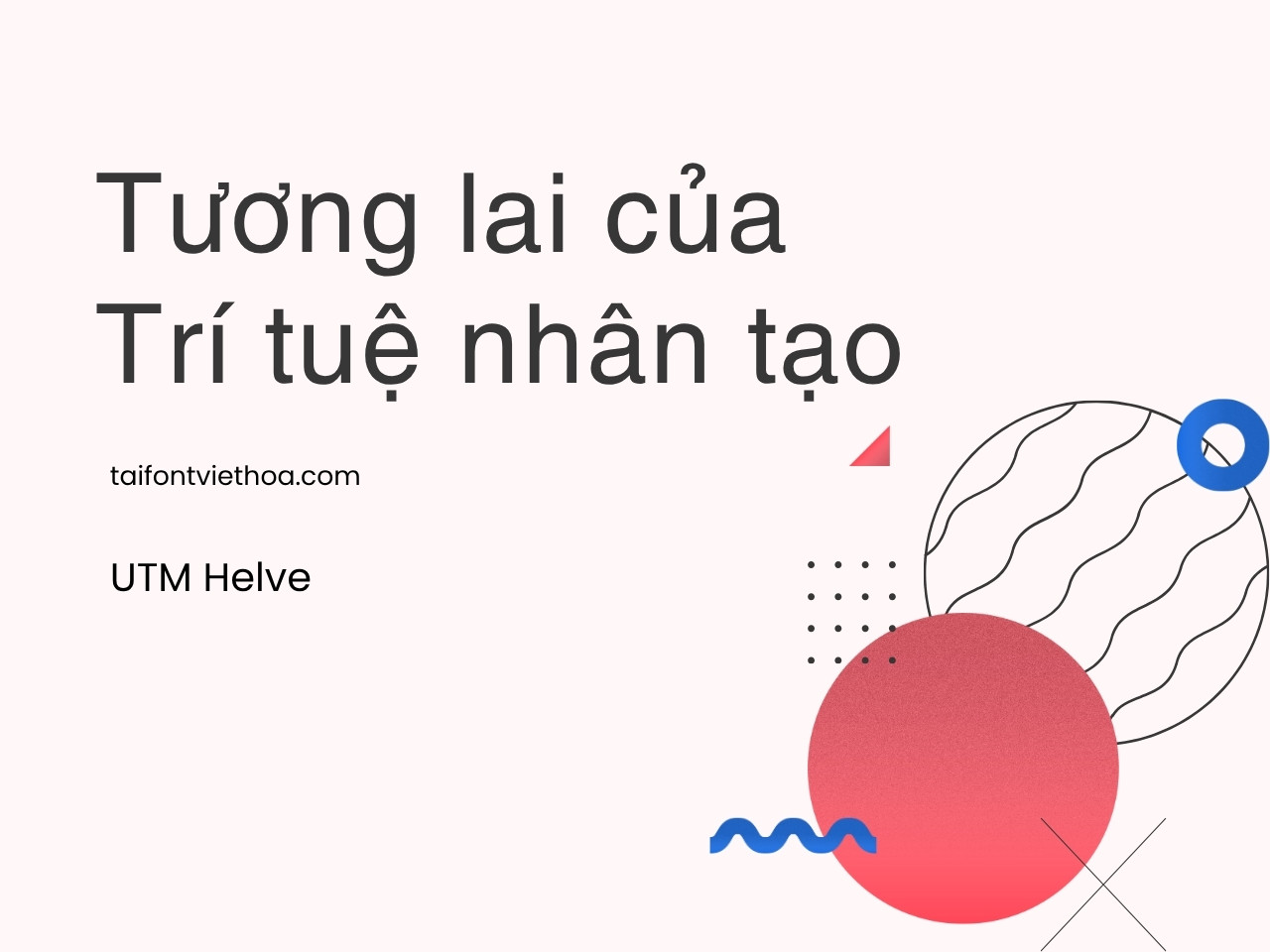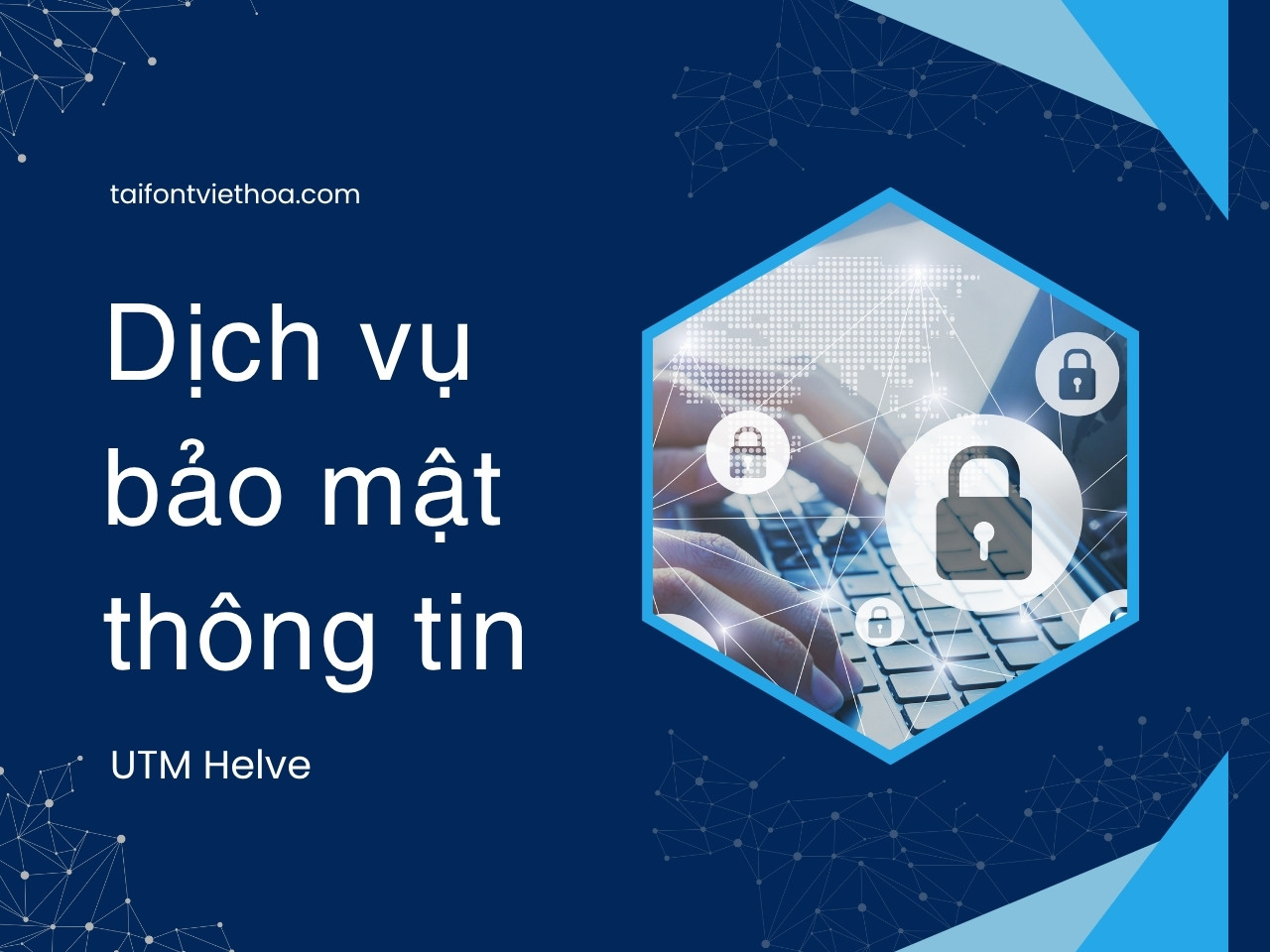
Font việt hóa UTM Helve
Giới thiệu về font UTM Helve
UTM Helve là phiên bản Việt hóa của font Helve – một kiểu chữ sans-serif hiện đại, tinh tế và rất được ưa chuộng trong thiết kế đồ họa và truyền thông. Font gốc nổi bật với các nét chữ thanh mảnh, đồng đều và dễ đọc, phù hợp cho nhiều ứng dụng từ nhận diện thương hiệu đến thiết kế website và in ấn. Phiên bản Việt hóa đã được hoàn thiện để hỗ trợ đầy đủ tiếng Việt cùng hơn 200 ngôn ngữ khác, mở rộng khả năng sử dụng trong nhiều dự án sáng tạo và chuyên nghiệp.
Giới thiệu về font UTM Helve
Đặc điểm thiết kế và ứng dụng của UTM Helve
UTM Helve sở hữu cấu trúc sans-serif không chân, với các nét chữ rõ ràng, thanh mảnh và cân đối. Font có thiết kế tối giản, giúp tăng khả năng đọc và phù hợp với nhiều kích thước và môi trường hiển thị khác nhau. Font thích hợp cho cả tiêu đề và nội dung văn bản dài, mang lại sự hiện đại và chuyên nghiệp cho các dự án thiết kế.
Font thích hợp sử dụng trong thiết kế website, nhận diện thương hiệu, quảng cáo, bao bì sản phẩm, brochure, poster và các dự án truyền thông đa phương tiện. Các ngành nghề phù hợp gồm: công nghệ, giáo dục, quảng cáo, startup và thương mại điện tử.